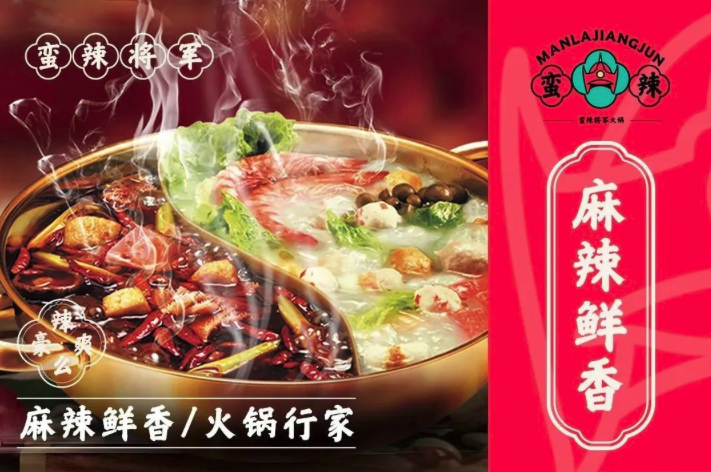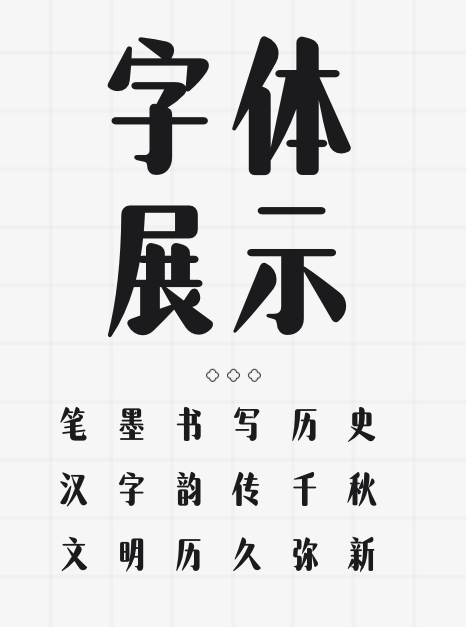
🔥塑造独特品牌风格,这三款字体让你秒变设计大神!🎨
在品牌塑造的征途中,字体选择绝对是不可忽视的一环!💡 一个独特的字体不仅能瞬间提升品牌形象,还能让你的品牌在众多竞争者中脱颖而出。今天,就给大家推荐三款堪称汉字之美的字体产品——神勇圆兔、荆轲简、将军令简,保证让你的品牌风格瞬间升级!🚀
1️⃣ 神勇圆兔 🐰
这款字体结合了传统与现代,圆润的笔画让人一见倾心。它的设计灵感来源于可爱的兔子形象,既灵动又不失稳重。💖 无论是用于儿童品牌、甜品店还是女性消费品,神勇圆兔都能轻松营造出温馨、亲切的氛围。让你的品牌在众多消费者心中留下深刻印象!💖
2️⃣ 荆轲简 🗡️
荆轲简以其独特的笔画设计和强烈的视觉冲击力,成为众多品牌青睐的对象。它的设计灵感来源于古代刺客荆轲的英勇与决绝,笔画刚劲有力,透露出一种不凡的气质。💪 这款字体非常适合用于男性消费品、运动品牌或高端奢侈品,能够瞬间提升品牌的档次和格调。💼
3️⃣ 将军令简 🏆
将军令简以其庄重、大气的设计风格,成为塑造权威、专业品牌形象的不二之选。它的笔画粗壮有力,线条流畅,透露出一种强烈的权威感和领导力。👑 无论是用于政府项目、大型企业还是教育机构,将军令简都能完美诠释出品牌的稳重和专业。让你的品牌在众多竞争者中稳坐头把交椅!👑